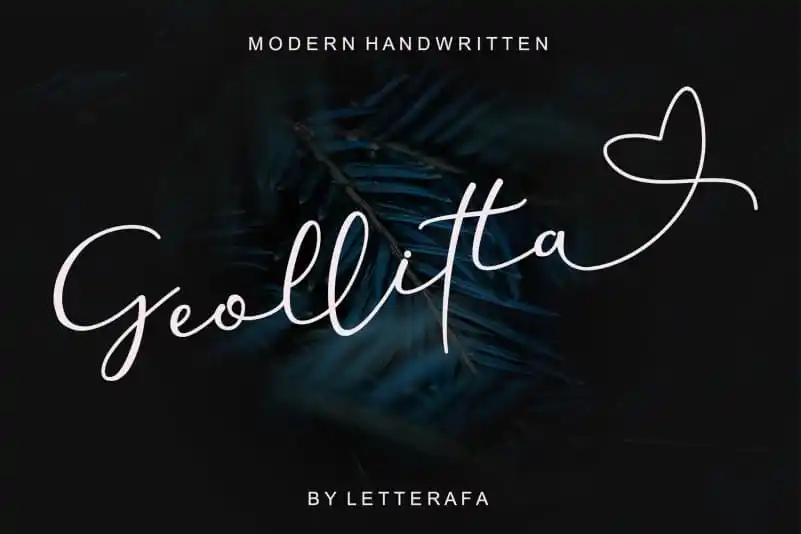
Geollitta Handwritten Font – Download Grátis
Geollitta é uma fonte de script feita a mão criada pelo designer Letterafa. Esta delicada fonte foi projetada para atender à necessidade de uma letra alegre e elegante, perfeita para ambientes como estabelecimentos de casamento, cartas pessoais, embalagens, design de livros e qualquer projeto DIY. Com suas letras fluidas que proporcionam um visual único e adocicado, Geollitta será um complemento perfeito para qualquer arte. Seja você criando uma identidade de marca impecável, projetando uma embalagem sedutora ou simplesmente adicionando um toque diferenciador a seu projeto, Geollitta está equipada para fornecer aquele olhar especial e único que o tornará um elemento notável no design. Seja você designer gráfico, criativo ou artesão, Geollitta é uma escolha ótima para aqueles que procuram fontes de script alegres, prontas para dar vida às suas criações.